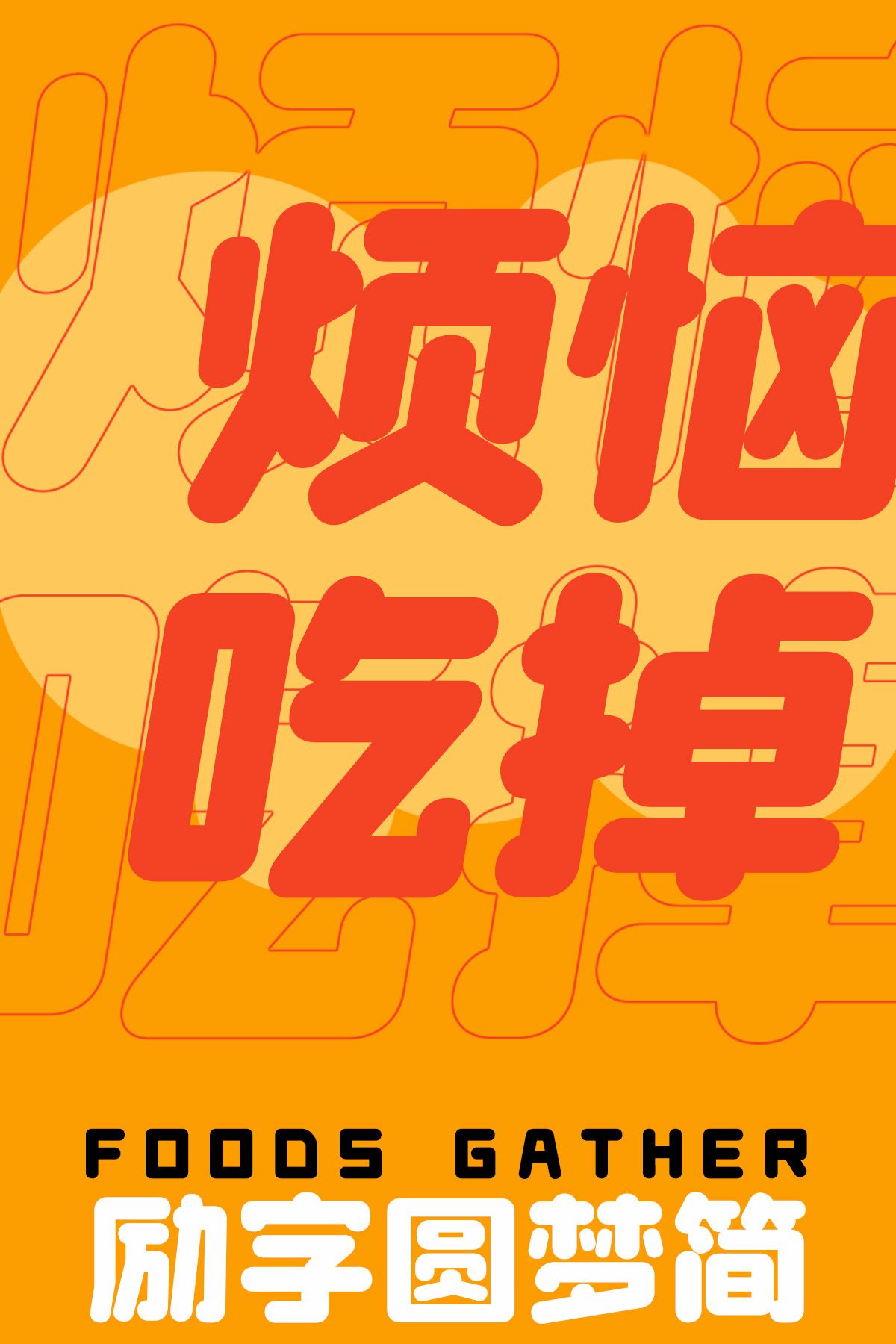
探索屏幕阅读的最佳伙伴——屏显字体推荐
随着数字阅读的日益普及,我们花费越来越多的时间在电子屏幕前浏览各种信息。从手机屏幕到电脑屏幕,从平板电脑到电视大屏,字体作为信息传达的载体,其选择变得尤为重要。今天,就让我们一起探索几款适合屏显的字体,为你的阅读体验加分。
励字开拓者简 特黑结合了现代审美与实用性,不仅字形美观,更在清晰度与易读性上表现卓越。其设计简洁而不失力量感,使得文字在屏幕上呈现得更加醒目。无论是在商务演示、广告宣传还是日常阅读中,励字开拓者简 特黑都能为观众带来舒适的视觉体验。
励字志向黑简 大粗融合了现代审美与传统韵味,字形刚劲有力又不失细腻之美。在屏幕上,它清晰易读,能够准确传达信息,同时赋予文本更深层的情感内涵。无论是设计海报、制作PPT还是日常阅读,励字志向黑简 大粗都能为您的屏显内容增添一抹独特的色彩。
励字粗圆简繁在保留传统韵味的同时,注入了现代设计的元素,使其既有古典之美又不失时尚感。在屏幕上,它清晰易读,视觉效果出众,能够迅速吸引观众的眼球。无论是用于品牌宣传、广告设计还是日常阅读,励字粗圆简繁都能为您的屏显内容增添独特的魅力。
励字圆梦简 大黑字型圆润柔和笔画为直线笔画,以竖折笔画代替部分弧线简洁明了。在屏幕上,它清晰易读,视觉效果优雅,能够迅速吸引观众的注意力。此款字体是具有3款字重的家族字体,适用标题和正文,具有良好的视觉表现与阅读体验。无论是用于商业展示、教育宣传还是个人创作,励字圆梦简 大黑都能够完美适应。
总的来说,选择一款合适的屏显字体对于提升阅读体验至关重要。以上几款字体各具特色,无论你是Windows用户还是Mac用户,都能找到适合自己的选择。